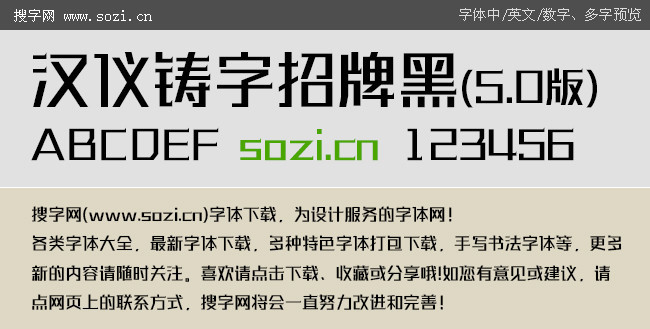
漢儀鑄字招牌黑5.0
搜字網(wǎng)提供一款漢儀鑄字招牌黑5.0中文字體下載,漢儀鑄字招牌黑在鑄字系列里面,這算是比較有個性的一款了,看起來比較簡約,很現(xiàn)代化,文字依然沒有弧度,風(fēng)格也偏向力量,給人的視覺感就是硬度比較大,同時,重心較低,顯得非常穩(wěn)重,能夠適用于藝術(shù)設(shè)計、包裝印刷、海報設(shè)計、圖形設(shè)計等領(lǐng)域。(如需要商用請聯(lián)系漢儀字庫購買版權(quán))